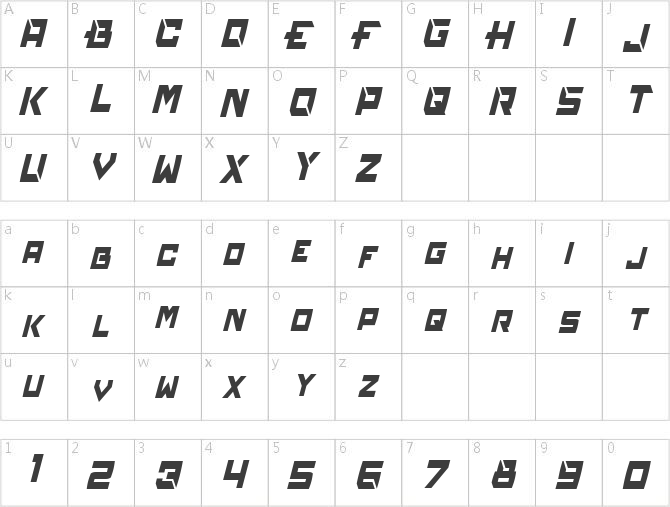
Reconstruct Condensed Italic
Reconstruct Condensed Italic介紹
Reconstruct Condensed Italic字體字庫是一款讓人賞心悅目、百看不厭的英文字體,適合各類廣告和產品包裝設計應用,字體大小0.03MB,格式為ttf字體,上傳用戶是13226568769,作者/版權方為未知